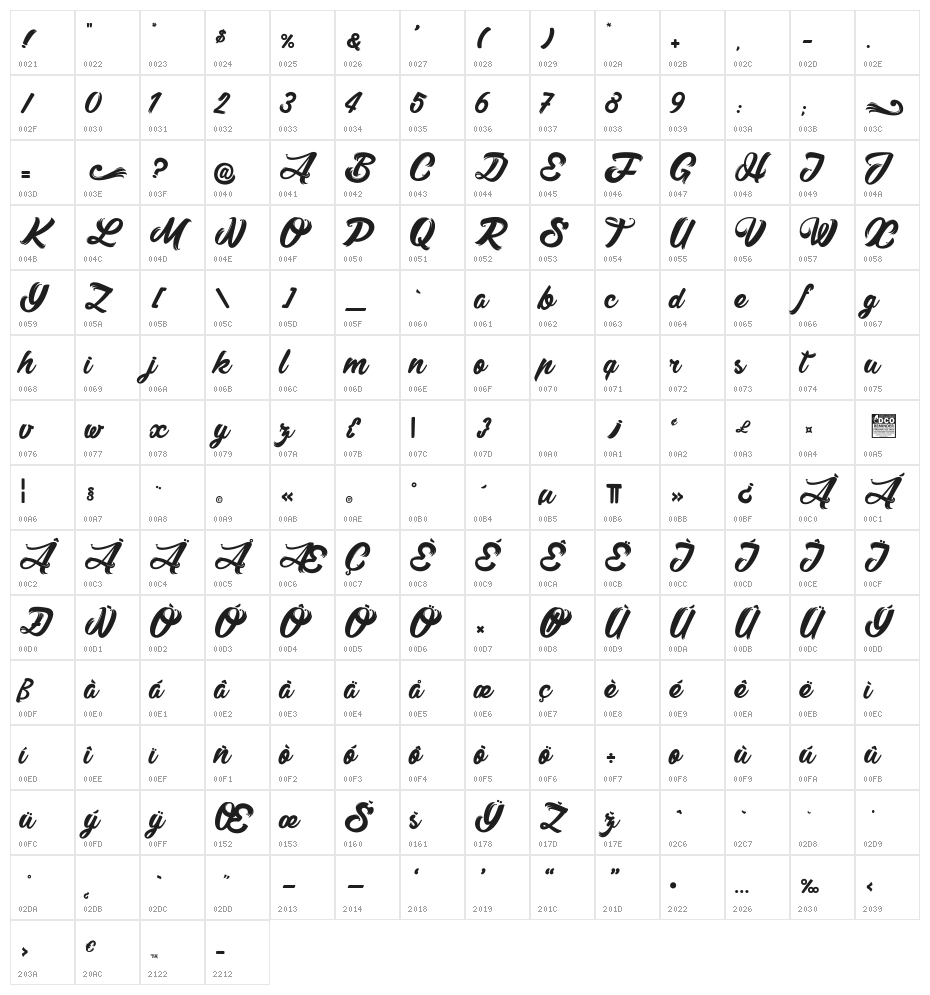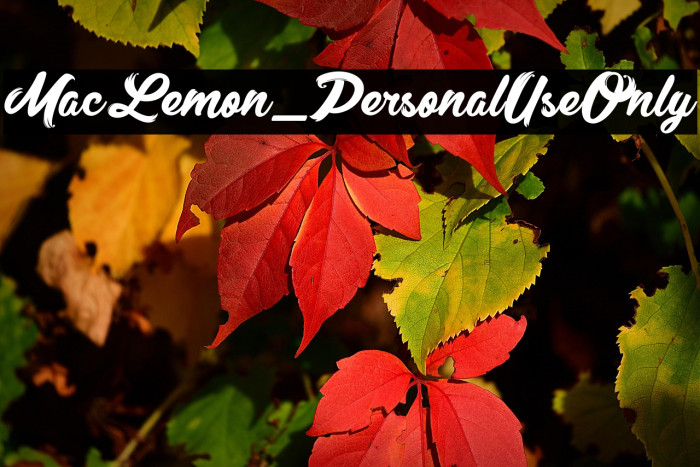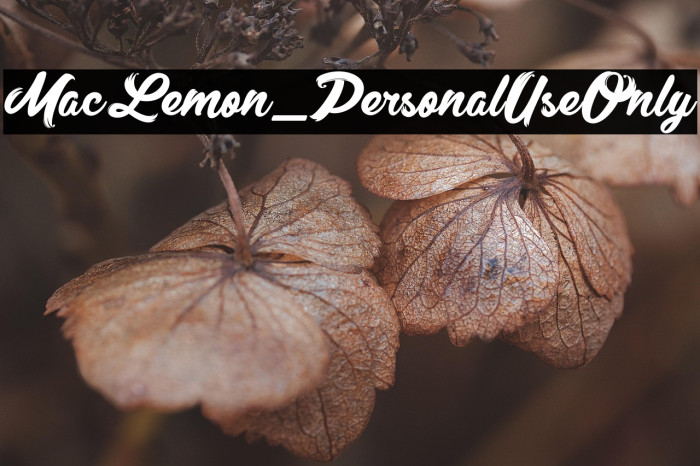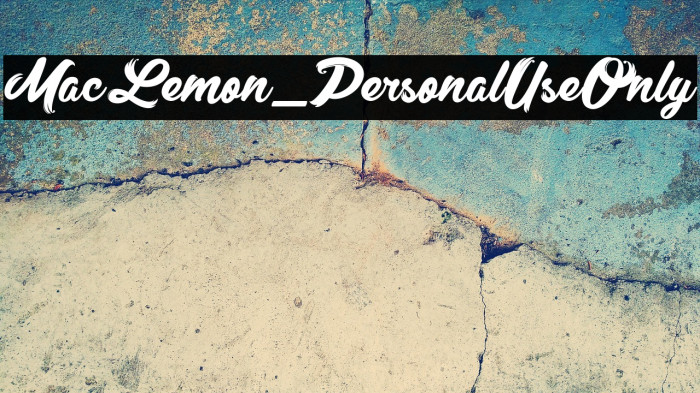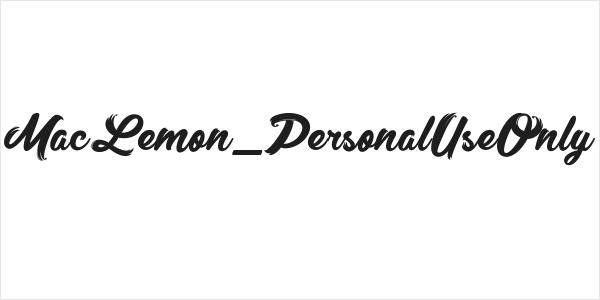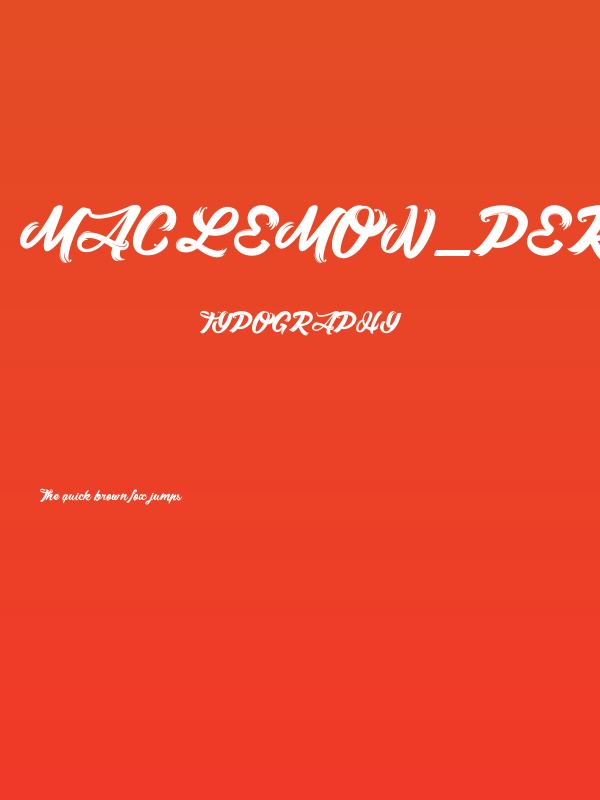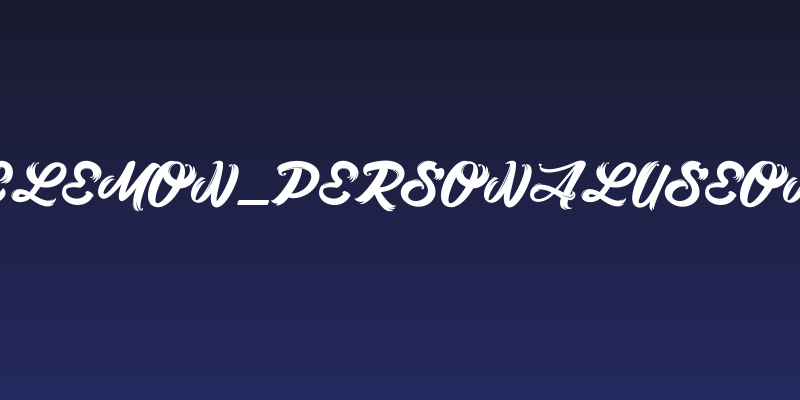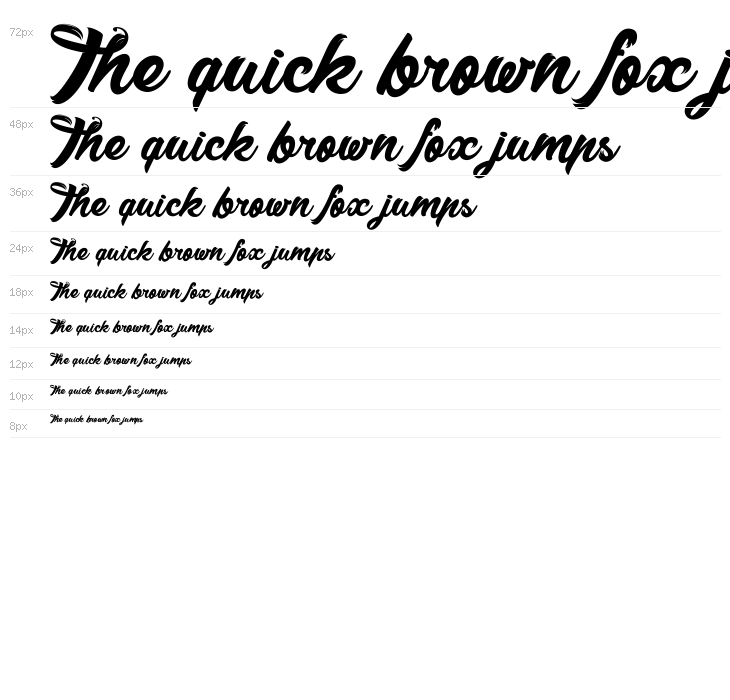
MacLemon_PersonalUseOnly Font
| 使用场景 | Logos, Headlines, Invitations |
| 推荐项目 | Ideal for branding, logo design, invitations, and headlines that require a bold and artistic touch. |